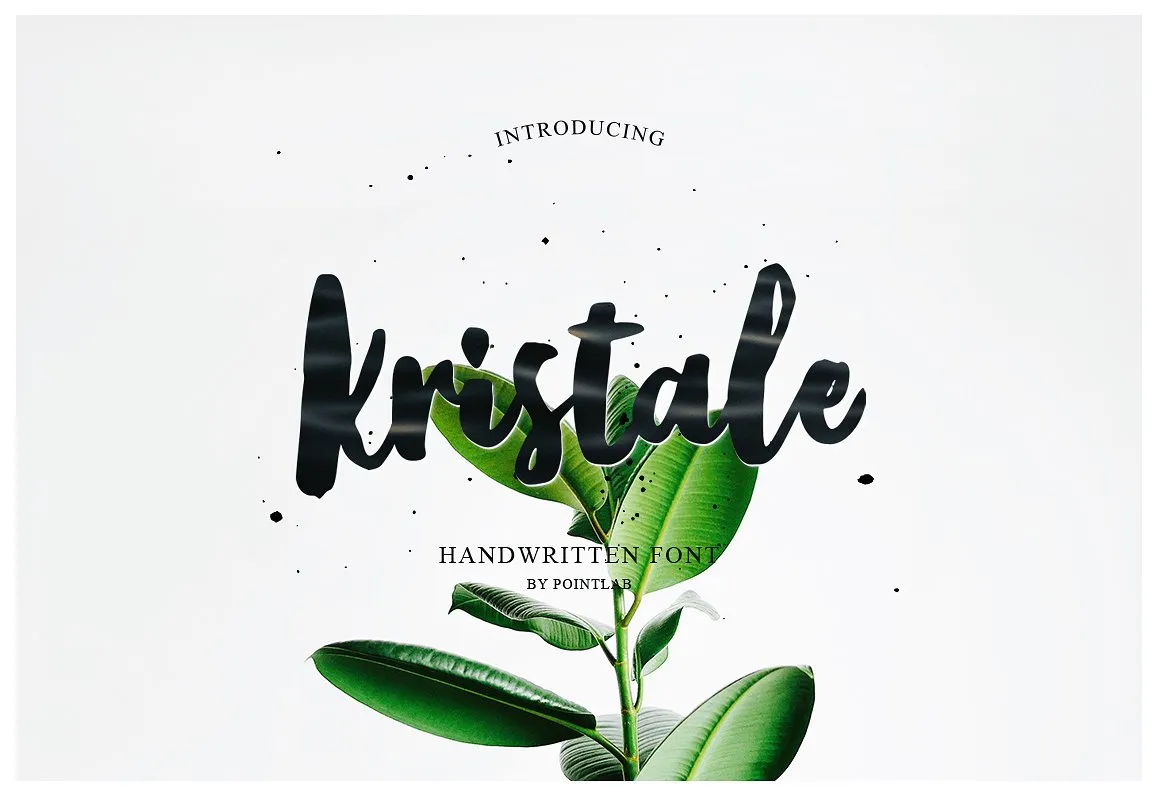
Kristale Script Font – Download Grátis
Descubra Kristale Script Font, uma nova opção para adicionar personalidade a seus projetos digitais. Introduzida pela pointlab, Kristale é uma brush script font com um estilo de calligrafia artesanal e caracteres decorativos, criando linhas que flutuam e dançam. Este tipo-fonte é perfeito para branding, decoração e criação de logotipos para sua casa ou escritório. Também ideal para cartões de convite casais, blogs pessoais, capas de livros, folhetos, marketing e até mesmo revistas. Com Kristale Script Font, você pode decorar qualquer projeto com uma pitada de elegância e criatividade.